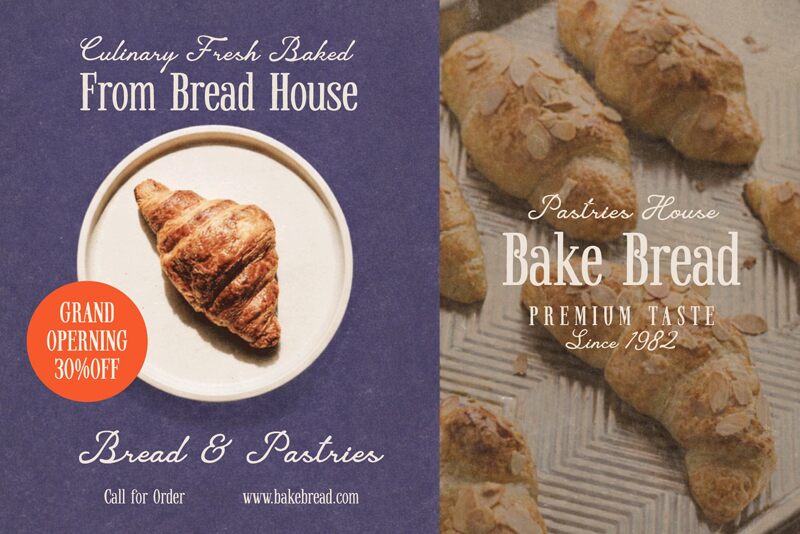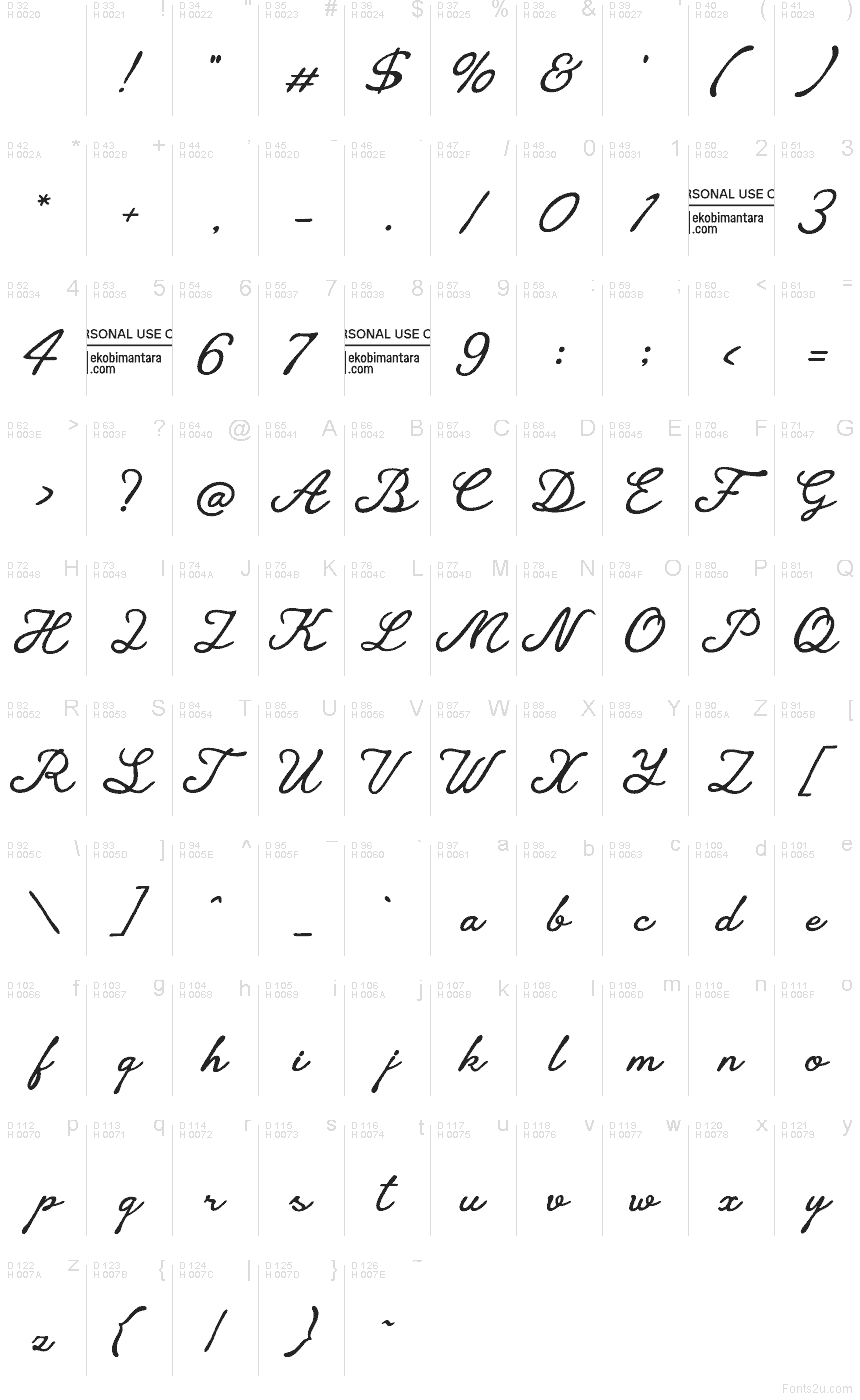
Salt Blue Script, zaprojektowany przez Eko Bimantarę, to darmowy odręczny krój pisma o płynnym zamachu osobistego pisma. Jego zmienna grubość linii, hojne pętle i połączone formy tworzą elegancką linię o swobodnym, żywym rytmie.
Marki działające w branży ślubnej i modowej mogą go używać do zaproszeń, opakowań kosmetyków oraz identyfikacji wizualnych z wdzięcznym, ręcznie robionym akcentem. W projektowaniu edytorskim jego szerokie łuki i ruch przypominający podpis pasują do nagłówków na okładkach magazynów oraz wstępów do artykułów o stylu lub uroczystościach.